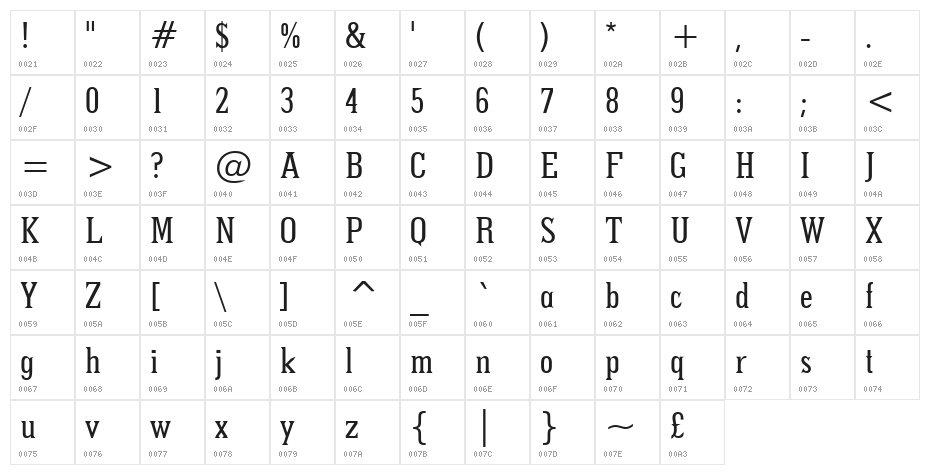
Pointed Font
| Kategorien | Serif |
| Gesamtstil | Classic |
| Anwendungsfall | Headlines, Logos, Editorial design |
| Vorgeschlagene Projekte | Ideal for editorial design, book covers, branding projects, and formal invitations where a classic yet modern serif is desired. |